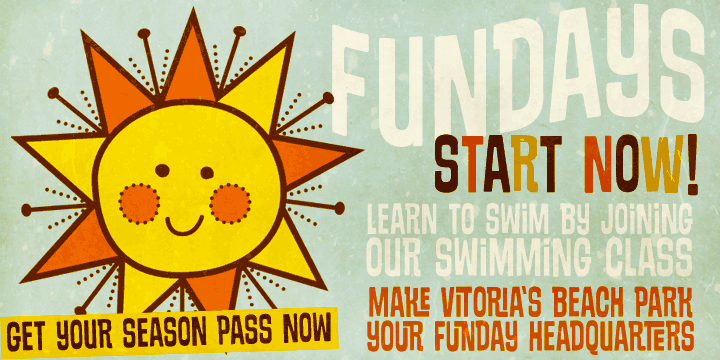
HI, giúp mình tìm font này với. tks
Các bác cho e xin family font "Arquitecta" của Latinotype đươc không ạ ? E tìm hoài mà ko có down free ^^! Cám ơn nhìu ạ !
- Đây là font thể loại Scribble thớt nhé, google nhiều kiểu lắm, cứ tìm tên loại này thì cả đống, còn gõ được dấu chắc hiếm :D
cho mình xin font này với
CHO MÌNH HỎI FONT CHỮ MY LIFE COFFEE CHỖ QUẦY TÍNH TIỀN (KO PHẢI TRÊN TƯỜNG) LÀ FONT GÌ VẬY?
Cái này là nhiều Font với kết hợp hình bạn ơi. Còn tìm Font ra giống hệt thì THUA.
Thái Châu: Kết hợp là sao hihi? Biết không chỉ em đi :)!
Một mớ hình ảnh lộn xộn lắp ghép, đc vài ba cái chữ là thuộc về font, sau đó tổng thể hết đống hình đó hỏi font gì. :v
có ai có font UVF tusj ko cho mình xin với, tìm hoài ko thấy
cái này bạn post trong hỏi tên font không lập topic mới gì gì đấy rồi mà nhỉ???
không ai giúp bạn ấy à. Mình font thì thì chịu.
Mình cũng post bên đấy mà vẫn chưa thấy ai giúp :">
Những Font này được Edit lại từ những Font Bold đậm bạn à. Còn kím Font giống hệt thì chắc không có rồi.
Bác ad có font này ko cho mình xin với
Swung Note
Sundowners
Caligo
Đòi toàn font trả phí :))